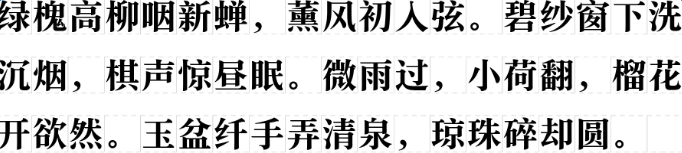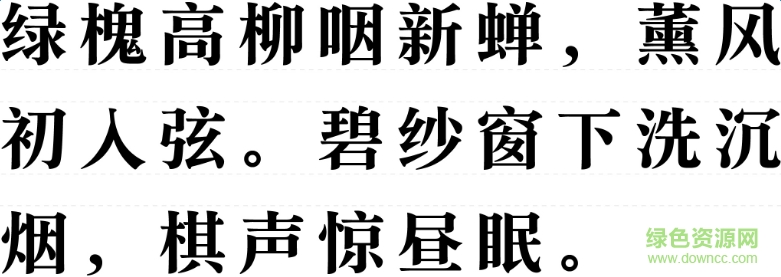
文鼎書苑宋是一款非常有特色的文鼎字體,這款字體跟經(jīng)典宋體相似,但又有其自身的特色,這款字體字形端正大方得體,非常適用于廣告設(shè)計(jì)、排版印刷等領(lǐng)域,喜歡的朋友歡迎來本站下載。
書苑宋是以現(xiàn)代宋體結(jié)構(gòu),融入更多楷體筆韻,兼容于電子閱讀的新概念設(shè)計(jì),讓人文的宋體調(diào)適于移動(dòng)閱讀。